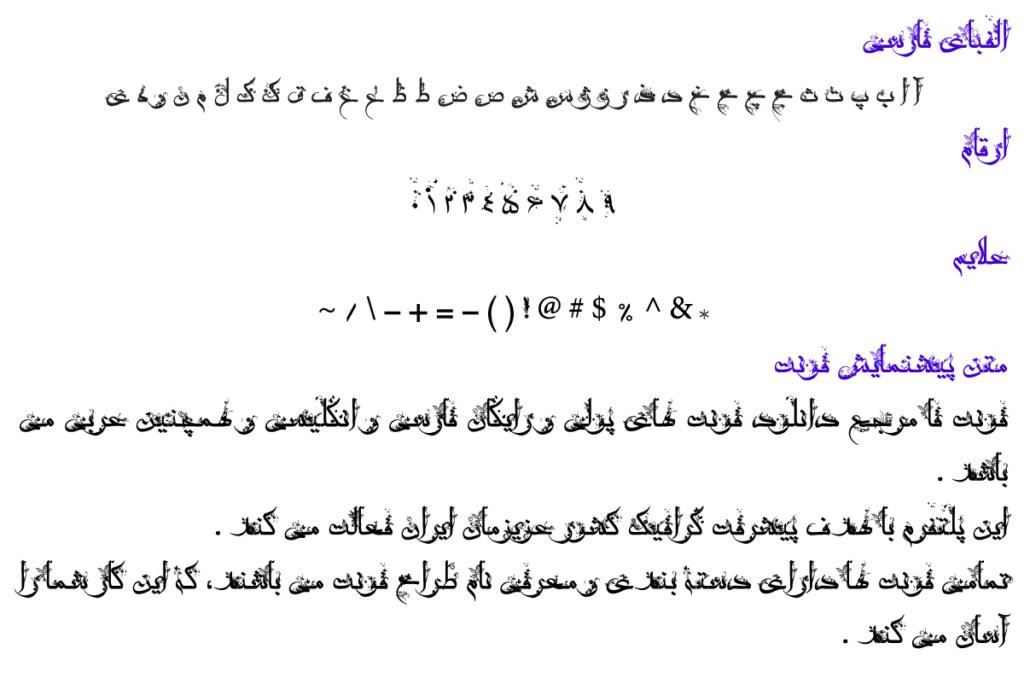
فونت فارسی گلدان – A Goldan
طراح فونت: توحید گلکارزاده نوع فونت: فونت فانتزی
توضیحات و معرفی فونت گلدان
فونت فارسی گلدان ( A Goldan ) از مجموعه فونت های آزاد می باشد، و نیز نوع فونت فانتزی می باشد.
فونت خوشگل مربوط توسط توحید گلکارزاده طراحی و ساخته شده است.
این فونت مشابه فونت گل است با این تفاوت که در این تایپ فیس روی کلمات گلهای زیبا کار شده است.